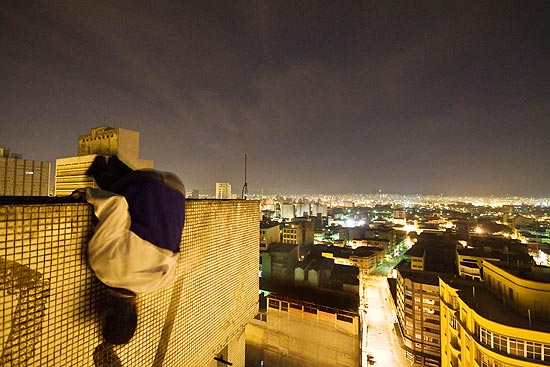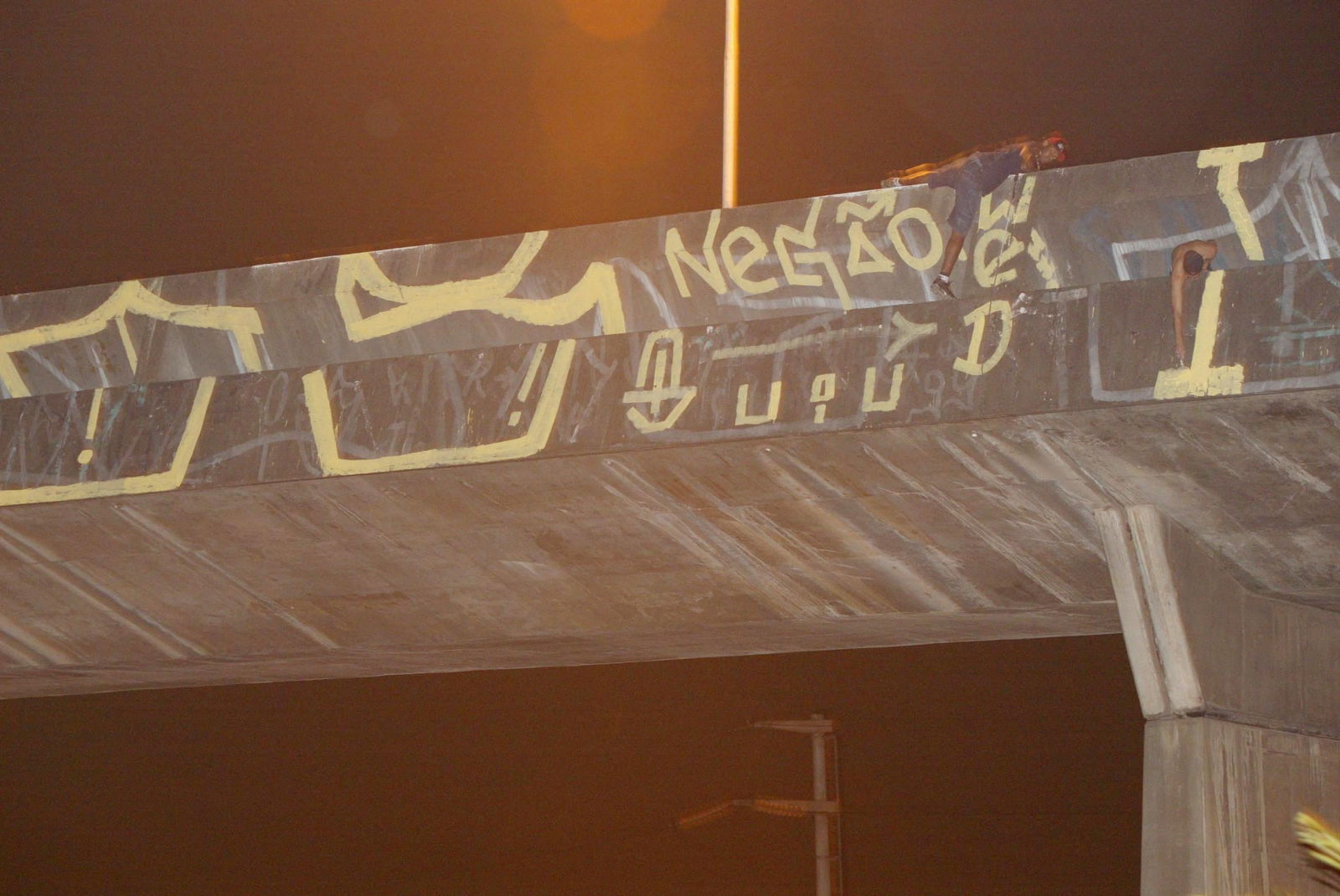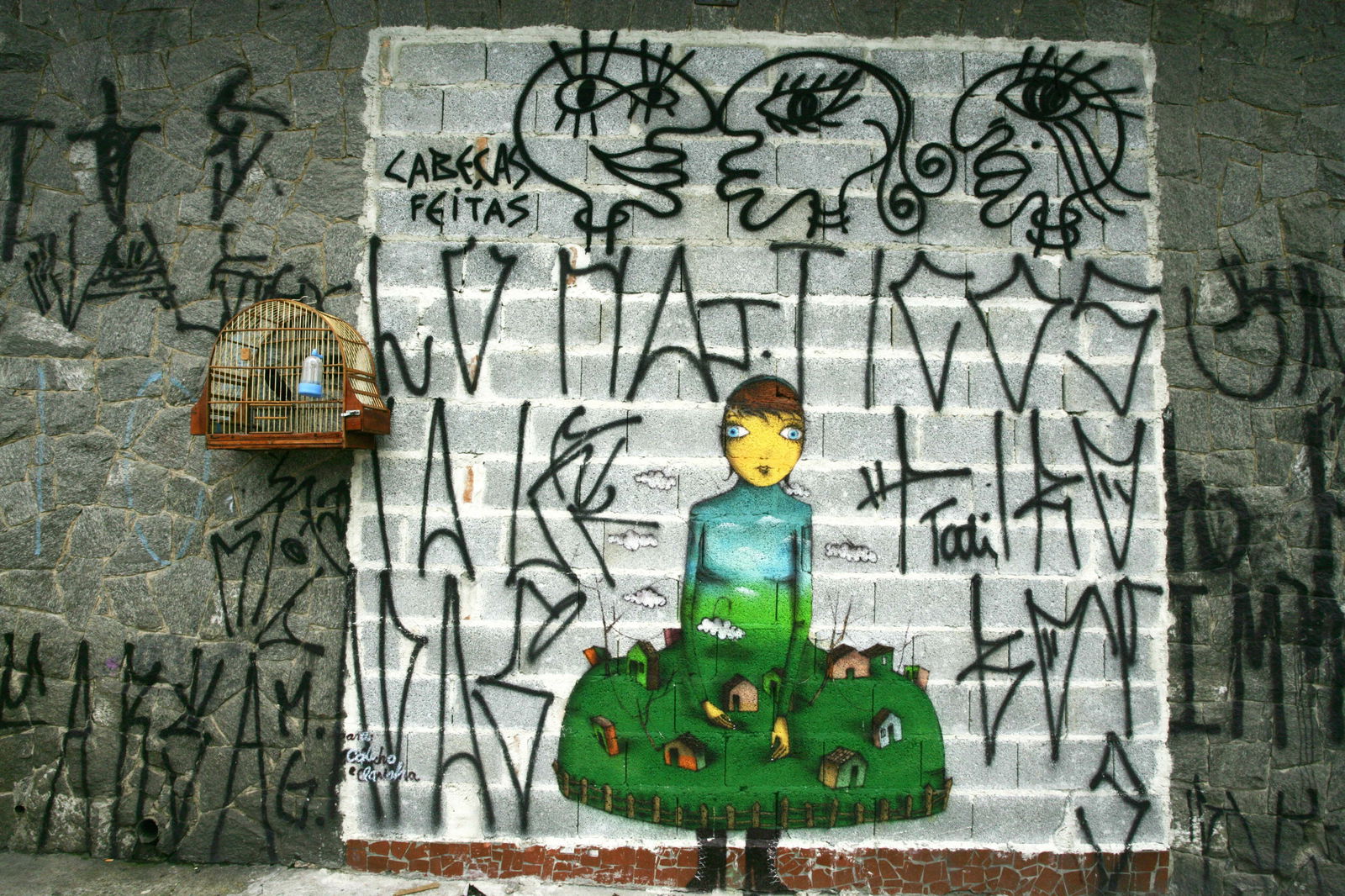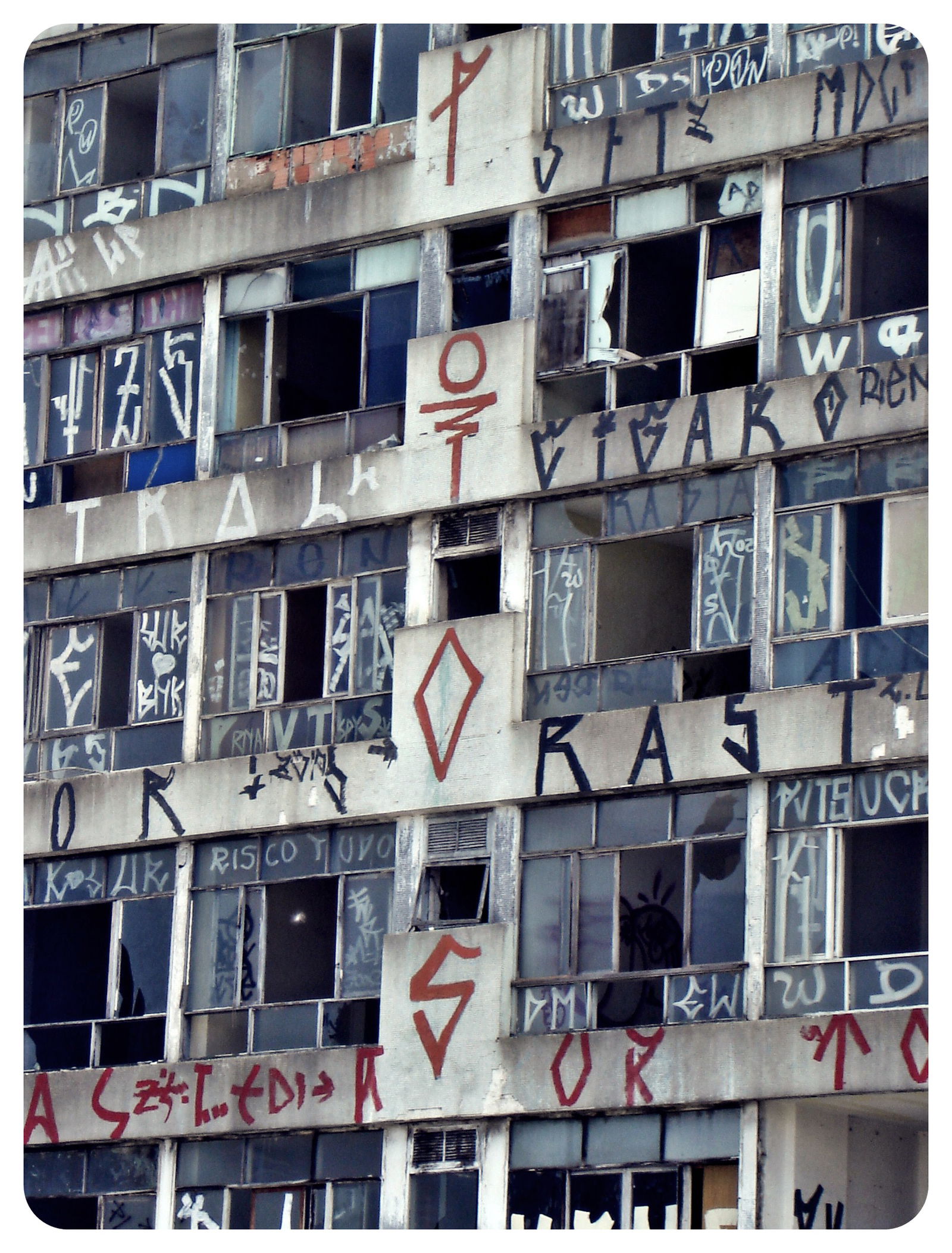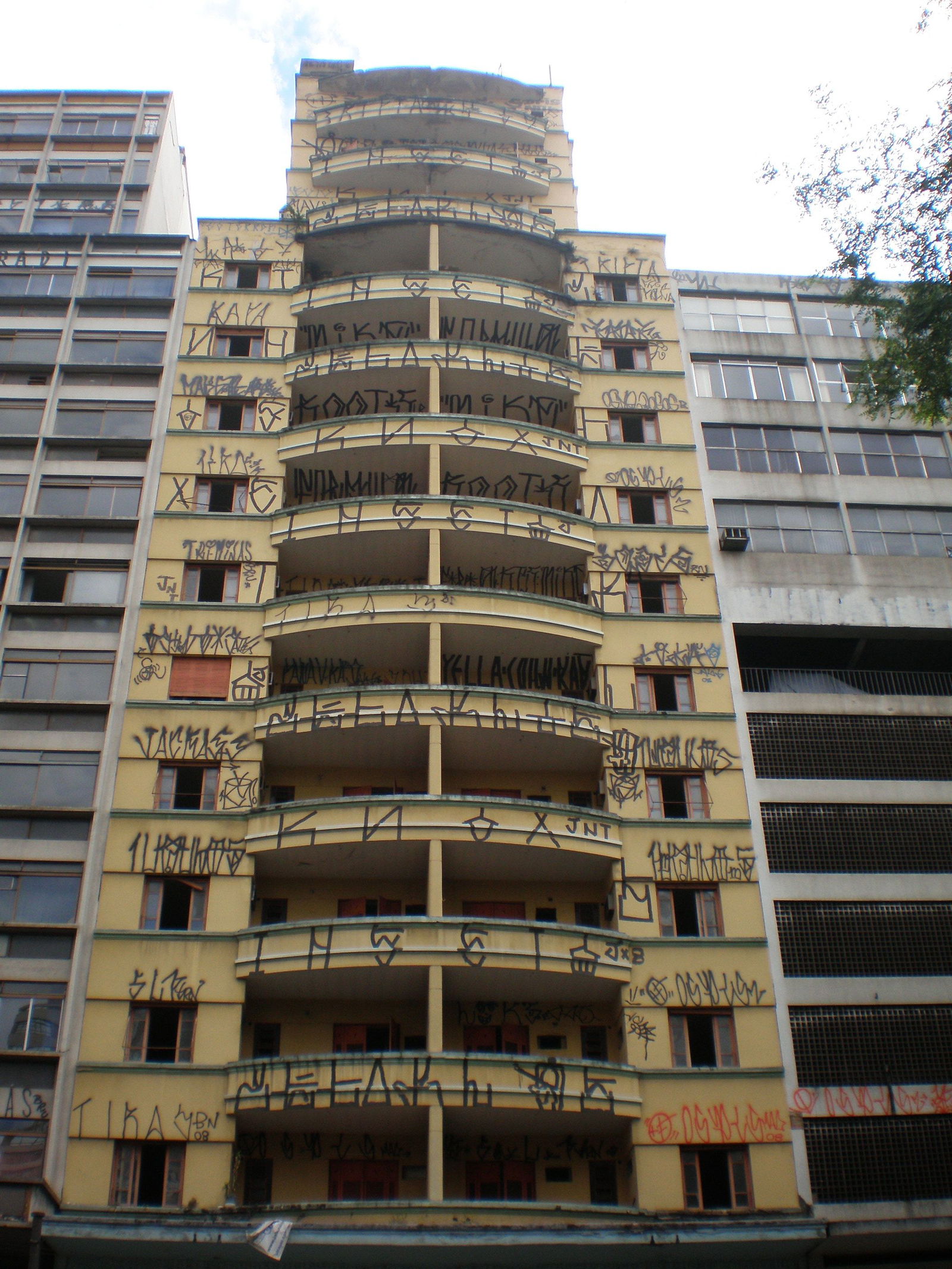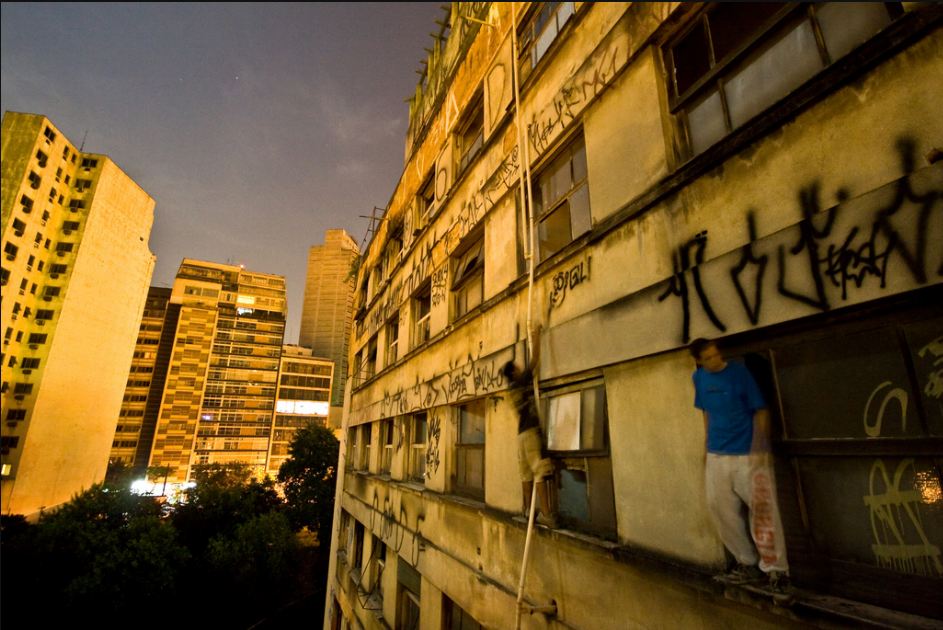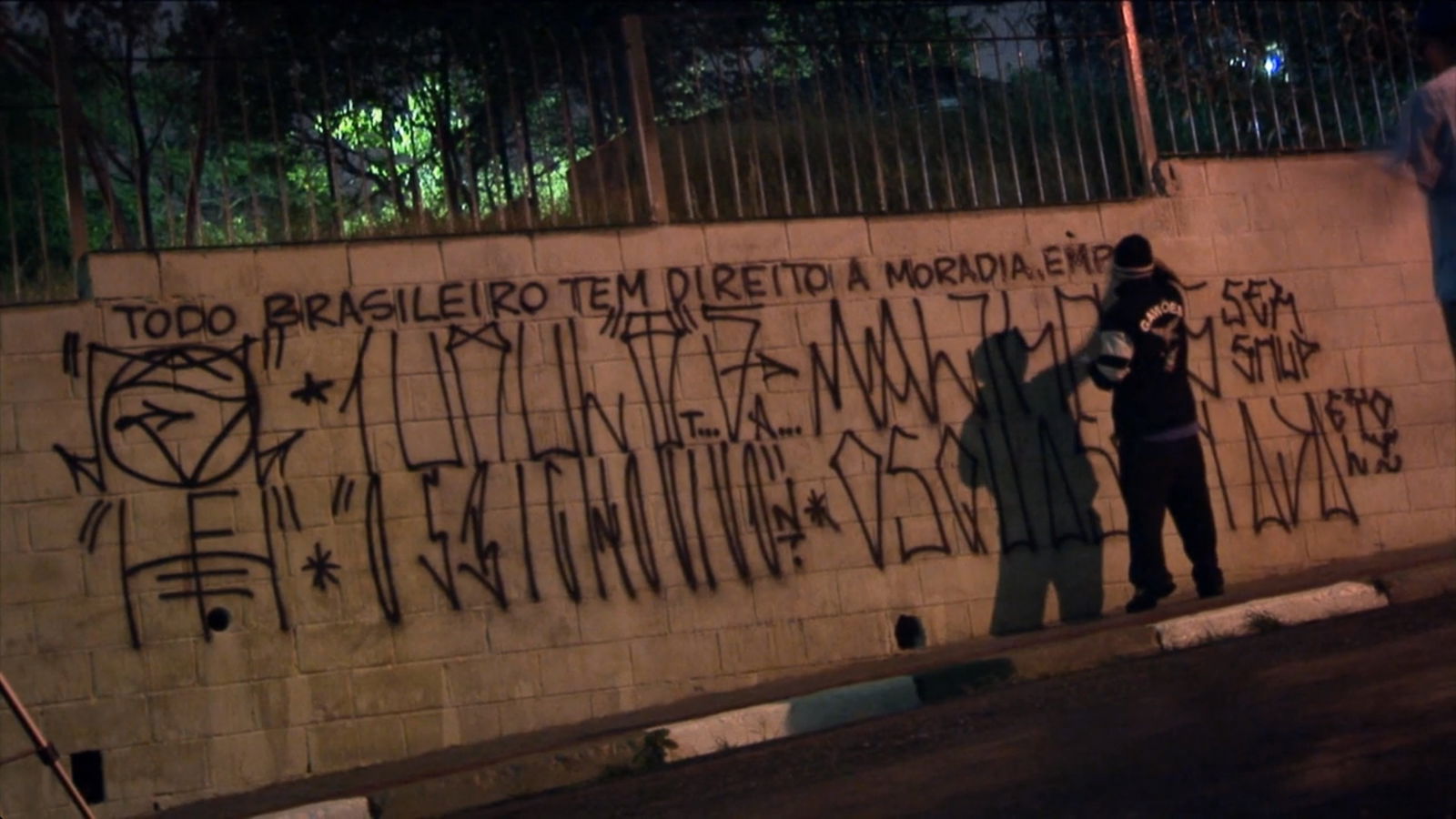
¿Vandalismo o lucha? La tipografía más arriesgada del mundo
¿Existe una razón por la que merezca la pena escalar un rascacielos sin arnés y cargado de botes de pintura?
Sao Paulo (Brasil) es una metrópoli de 21 millones de habitantes, centenares de anchas avenidas y un número incontable de edificios que superan la treintena de niveles. También, o quizás por eso, es un mural sin límites para unas bandas oriundas de esta urbe que graffitean cada rincón de la ciudad con su genuina y monocromática tipografía. Se llaman pixadores. El pixação, su estilo, cumple la paradoja de ser su manera de jugarse la vida, y a su vez, su más valiosa razón para vivirla
Se hace difícil dar un paseo por este gigante sudamericano sin toparse con cientos de estos escritos por todos los rincones donde uno mire. Muros, balcones, puentes, túneles, cornisas, vallas, monumentos, tableros de canastas, fachadas de comisarías y hasta en inverosímiles paredes planas de decenas de metros de altura. No importa lo inaccesible que sea el espontáneo lienzo, un pixador, llega.
Estos spiderman de bote son bandas de jóvenes procedentes de la periferia de la ciudad, en su mayoría de clases sociales marginales, que plasman cada noche su tipografía única en el mundo por cada resquicio. Las prisas las llevan porque su mensaje debe estar terminado antes de que empiecen a sonar las sirenas de policía.
Para la gran mayoría de la población se trata de vándalos, delincuentes que ensucian los muros con palabras ininteligibles de dudoso gusto artístico. Ellos se valoran como creadores comprometidos con una alta dosis de riesgo en su trabajo. Su actividad, según afirman, es el resultado de una reacción contra la exclusión social que lanzan en territorio de las clases acomodadas.
El pixação nació en Sao Paulo en los años 80 como un modo de expresión gráfica urbana que tomaba el testigo de las pintadas protestatarias de los años 60, cuando grupos sindicales decoraban la urbe a base de tinta durante la dictadura militar brasileña. Se trata de mensajes monocolor, escritos con una tipografía propia, que recuerdan a las letras picudas de los alfabetos bárbaros que se utilizan en las portadas de muchos discos heavy metal. Escaleras humanas, tuberías colgantes, alargadores caseros para plasmar la pintura. Ningún riesgo es demasiado para ejecutar esta modalidad pictórica.
Para tratarse de mensajes sociales, es casi imposible lograr leer su significado, pero este hecho no ha sido motivo suficiente para que las crews, como se denominan a las bandas rivales que practican la tarea, sigan incorporando nuevos miembros que reproducen y entienden al detalle cada figura, cada vocablo y cada concepto.
Su mayor preocupación no es “que la sociedad les acepte”, como afirma un joven pixador en un vídeo promocional de la marca Puma que habla de ellos, sino lograr alcanzar la gloria al dejar su grito gráfico en el lugar más inverosímil posible. Un rincón aún más difícil que el que hayan alcanzado sus rivales pintores. Ese lugar, donde la sociedad a la que interpelan no pueda pasar por alto su desafiante hazaña.
Los documentalistas João Wainer y Roberto T. Oliveira retratan a estos jóvenes en su trabajo PIXO, donde tratan de mostrar sus múltiples caras: La humana, la luchadora, la reivindicativa, la artística y la vandálica.
Según palabras de los creadores a la periodista María Martín, el pixação debería ser considerado “un bien inmaterial de la ciudad. La sociedad tendría que intentar entender que esos jóvenes de la periferia abandonados por el Estado prefieren ser odiados que ignorados”.
Pocos habitantes de la zona urbana de Sao Paulo están muy de acuerdo con eso, pero es precisamente esa polémica la que materializa su objetivo. Se habla de ellos. Instituciones, marcas, críticos y público no llegan a concretar si lo que hacen es bueno o malo. Así, marcas deportivas como Puma los promocionan en sus campañas mientras la ley brasileña endurece las penas contra sus acciones. Un hecho que no impide, por ejemplo, que algunas de las equipaciones oficiales de la selección brasileña de fútbol lleven los nombres de los jugadores escritos en una tipografía claramente inspirada en su estilo.
Provocar es su esencia. Ni siquiera fueron capaces de poner límite a su espíritu iconoclasta en la Bienal de Berlín del año pasado ni en la de Sao Paulo del 2008.
En la primera, un grupo de pixadores que habían sido invitados al evento internacional decidieron vulnerar las normas del acto, para el cual debían pintar en unos paneles blancos que los organizadores habían colocado dentro de St. Elisabeth, una iglesia protegida, y acabaron escalando los muros internos del edificio para plasmar sus mensajes en las propias paredes del santuario.
En aquella ocasión incluso el desesperado organizador del acto acabó embadurnado en pintura al tratar de evitar el suceso. Algo similar ocurrió en la Bienal celebrada cuatro años antes en Sao Paulo, a la que ni siquiera estaban invitados.
40 pixadores irrumpieron en el recinto y comenzaron a vaciar sus aerosoles en las paredes del segundo piso, donde se desarrollaba la Bienal, ya que en esta ocasión los productores habían dispuesto paredes en blanco como un espacio teóricamente abierto a intervenciones artísticas libres. En aquella experiencia, que acabó con detenciones, uno de los jóvenes había escrito: Abajo la dictadura, una alusión al arte contemporáneo mainstream que infravalora su capacidad creativa,